小林章.
亚太区字体总监
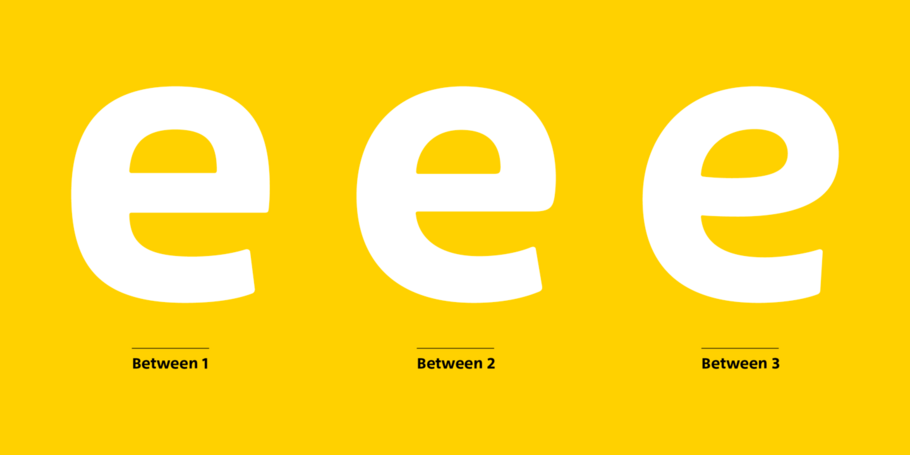
他如是说
“
记住这件事很重要:字母不是独立存在的,它们必须相互搭配才能形成单词。当字母造型无法让我满意时,我会相当随意地对其进行更改。”
字体创意总监小林章拥有三十年的工作经验,在日文字体设计方面拥有丰富的背景,并且对书法有着深刻的理解。在东京武藏野美术大学学习了四年之后,小林章在照相制版制造商写研公司接受了他的第一份工作。在那里,他参与了日文字体设计漫长而复杂的流程。
离开这一职位后,他在伦敦印刷学院学习西文书法,成为一名自由职业的字体设计师。2002 年,小林发布了 Optima Nova——Hermann Zapf 所设计的 Optima 的现代化版本,并在 2009 年和 Adrian Frutiger 合作,升级了 Frutiger 的同名字体家族。最近,小林章主导了 Monotype 首个原创日文字体 Tazugane Gothic 的开发工作。小林章在职业生涯中设计了 50 多个字体家族,包括 DIN Next、Akko Pro 和 Neue Frutiger,并与索尼、瑞银和松下等主要品牌进行了合作。
Between™
一款字体以3种方式呈现。
DIN Next™ Slab
结实的方形衬线体。
Akko®
灵活、巧妙而时髦。
描绘出具有Isonorm™设计般的超强字体。现在,将它与诸如Cooper Black™字体的有机设计融合在一起。正是这两种设计概念的融合启发了Kobayashi绘制出Akko。
Kobayashi说:“我最初的想法是创建一种具有柔焦(soft-focus)效果的无衬线字体。从这里开始,设计演变为两个系列:结实、井井有条的无衬线体Akko及柔和、友好的Akko Rounded。”